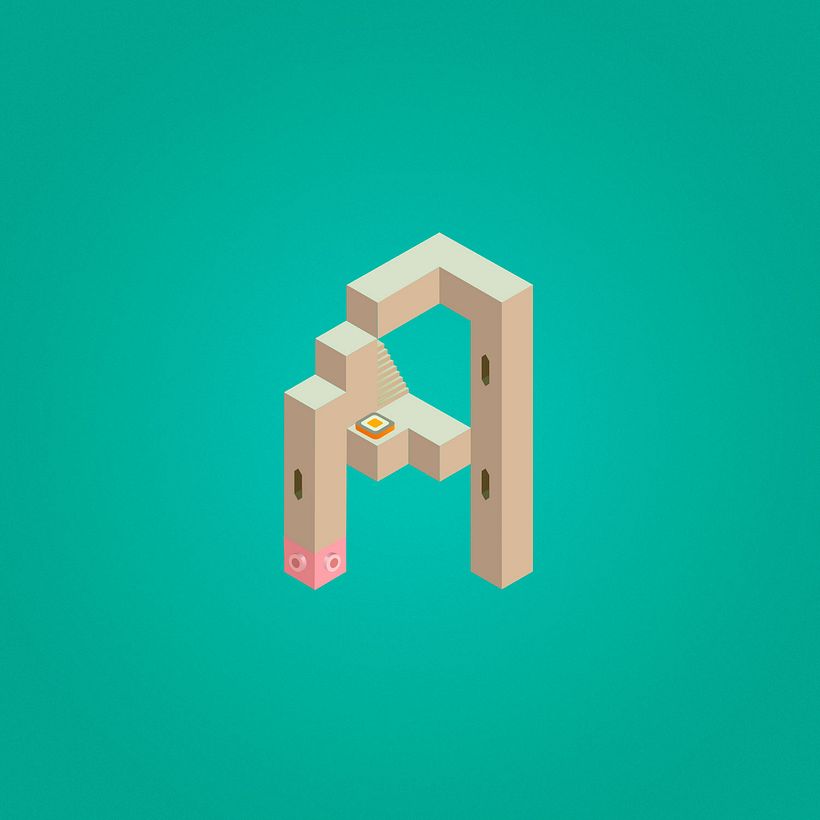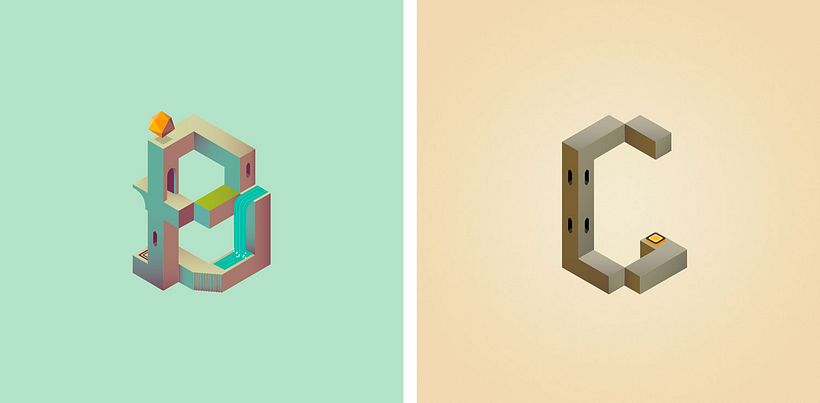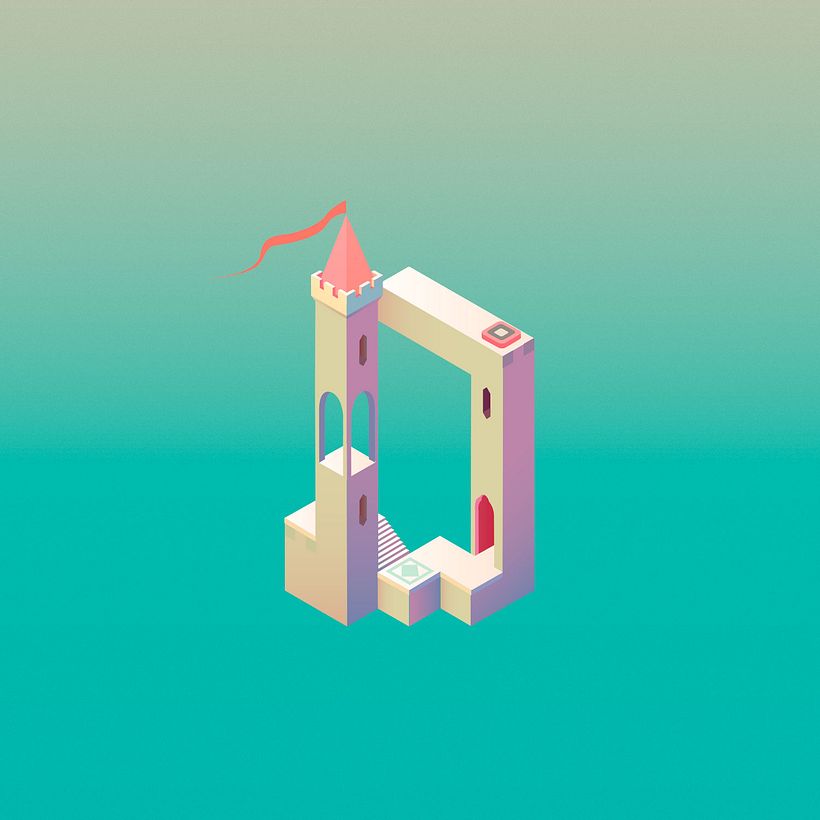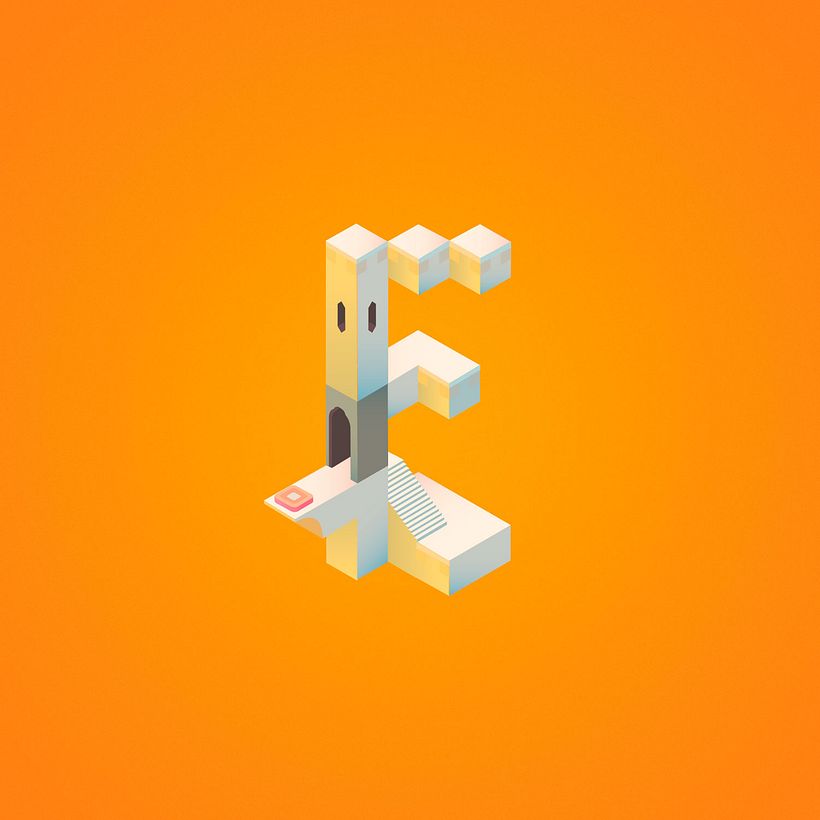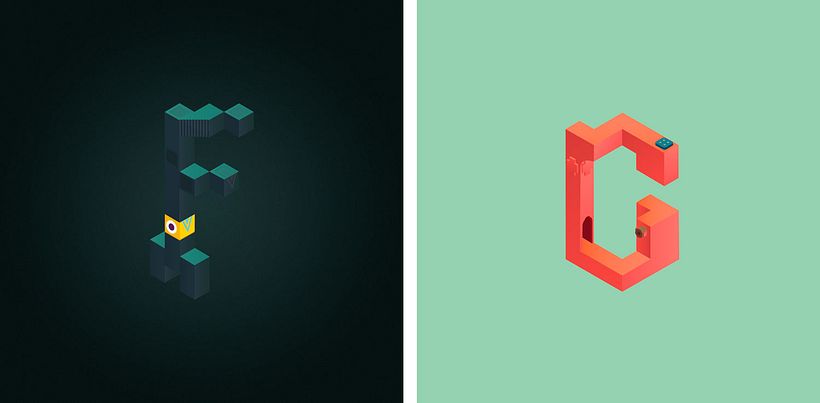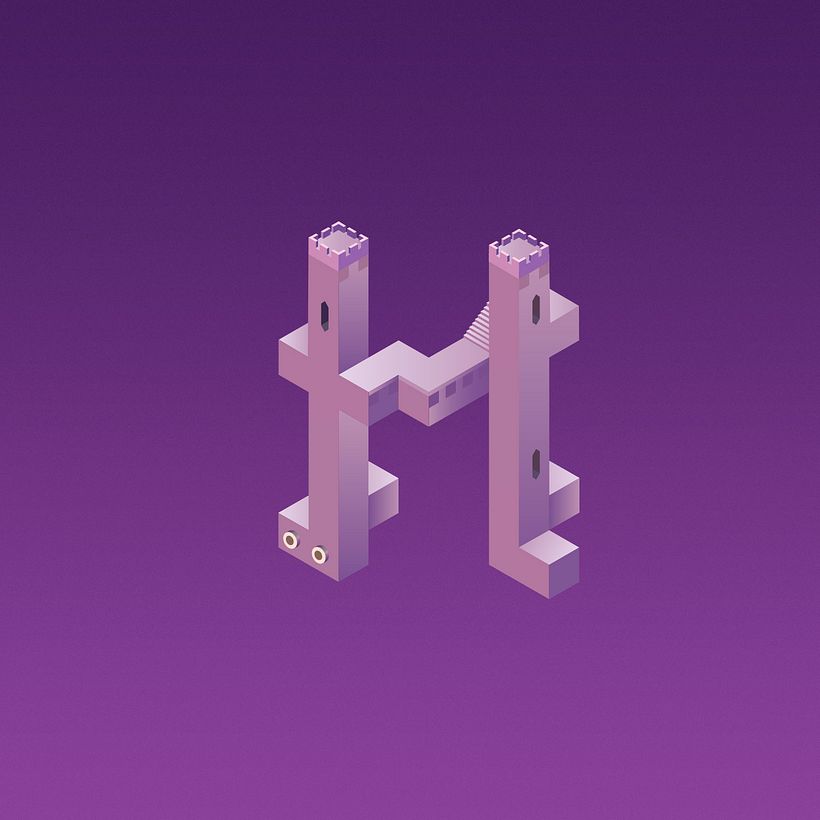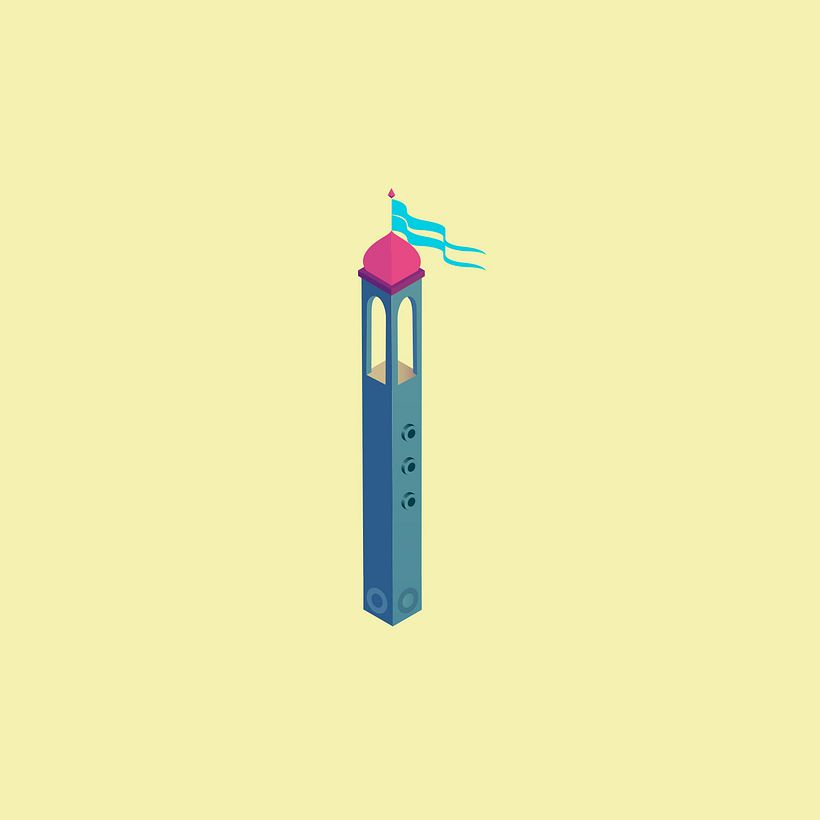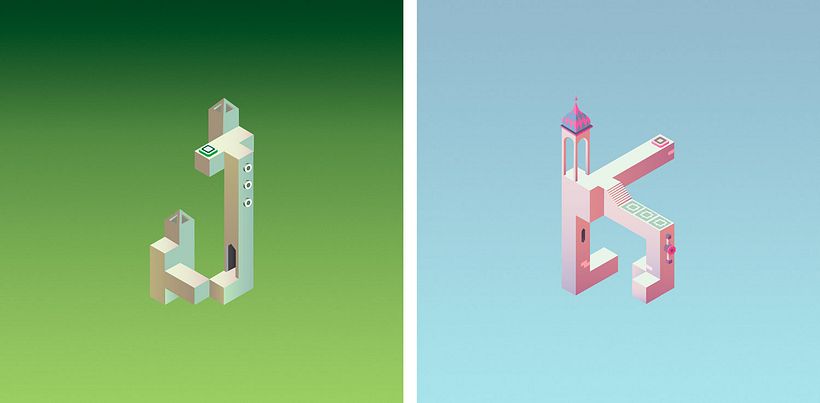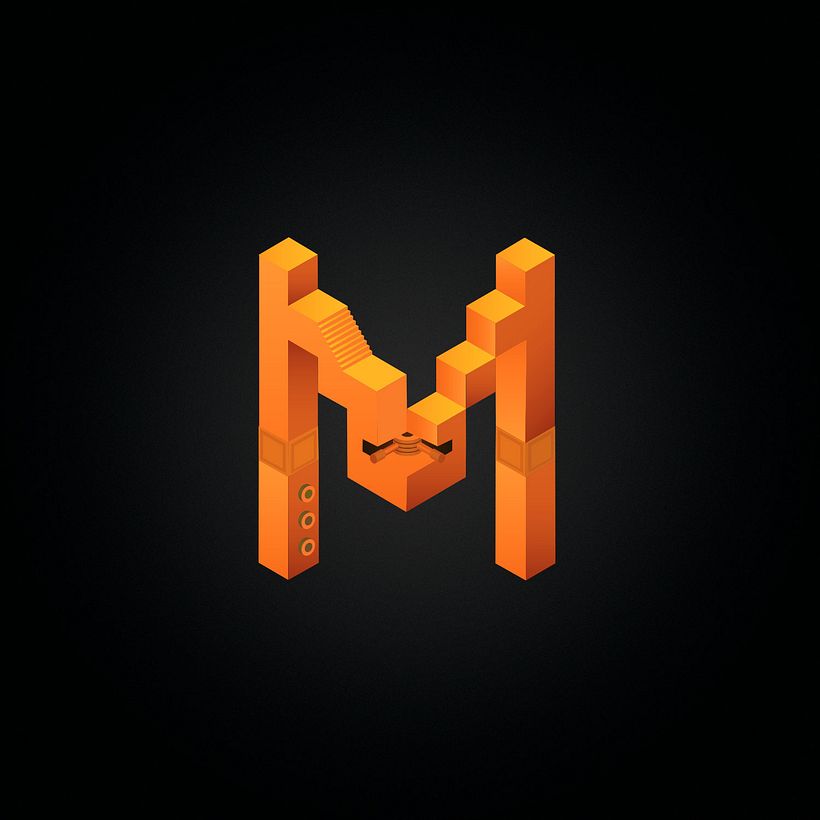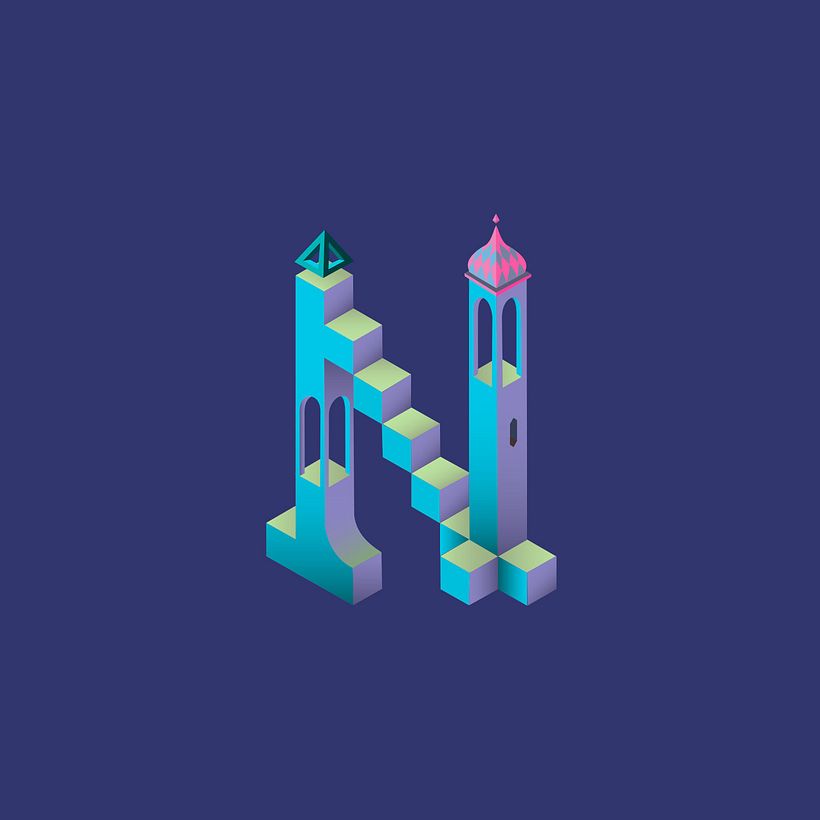
Alphabet Valley, la tipografía basada en Monument Valley
Arquitectura imposible, letras y multitud de efectos ópticos son los ingredientes para este proyecto tipográfico.
Si no has vivido bajo una piedra durante los últimos años, probablemente conozcas Monument Valley, un juego de lógica y aventura, basado en la arquitectura imposible de Escher, cuyo objetivo es llevar a una princesa hasta un lugar seguro. El juego, disponible únicamente para smartphones y tabletas, tuvo muchísimo éxito, en gran parte, gracias a su precioso diseño minimalista. Claudia Musett, una diseñadora de Barcelona, inspirada por sus mundos mágicos y la geometría de sus formas, ha creado su propio "Alphabet Valley", un abecedario compuesto por las formas arquitectónicas imposibles de Monument Valley.
Igual que ocurre en el juego, las letras creadas por Claudia Musett están formadas por figuras geométricas que, combinadas, presentan la forma de edificios poco probables. No sólo la forma de las letras, creadas a partir de intrincados efectos ópticos, es un más que logrado homenaje a este juego de culto, las paletas de colores y los degradados están realmente conseguidos, hasta el punto que no resultaría extraño encontrarse con la princesa Ida tratando de descifrar el camino correcto para alcanzar el siguiente nivel.
Cada una de las letras de Alphabet Valley está basada en un nivel del juego. Algunos, según han admitido los propios creadores, sólo aparecen en la versión beta de la plataforma; esto da una idea de la inmersión de Claudia Musett en el proyecto. Una inmersión que responde al perfil multidisciplinar de la diseñadora barcelonesa. En su portfolio es fácil entrever que la creatividad está presente en todos sus trabajos; la ejecución, salta a la vista, también es sobresaliente.
Claudia Musett, cautivada por la belleza de Monument Valley, decidió diseñar una tipografía basada en el juego.